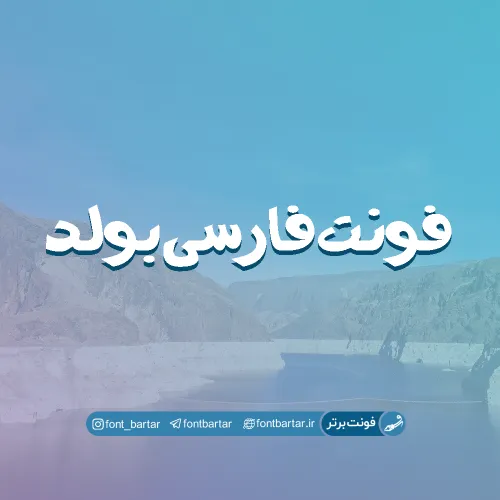
فونت فارسی بولد
فونت فارسی بسیار زیبا و گرافیکی بولد ، این فونت بسیار کاربردی در صورت استفاده مناسب می تواند زیبایی کارها را دو چندان کند.
فونت بولد مورد استفاده برای:
- طراحان وب سایت و گرافیست های خلاق می توانند از این مجموعه زیبا فونت در طراحی پروژه های تبلیغاتی و تجاری خود کمک بگیرند.